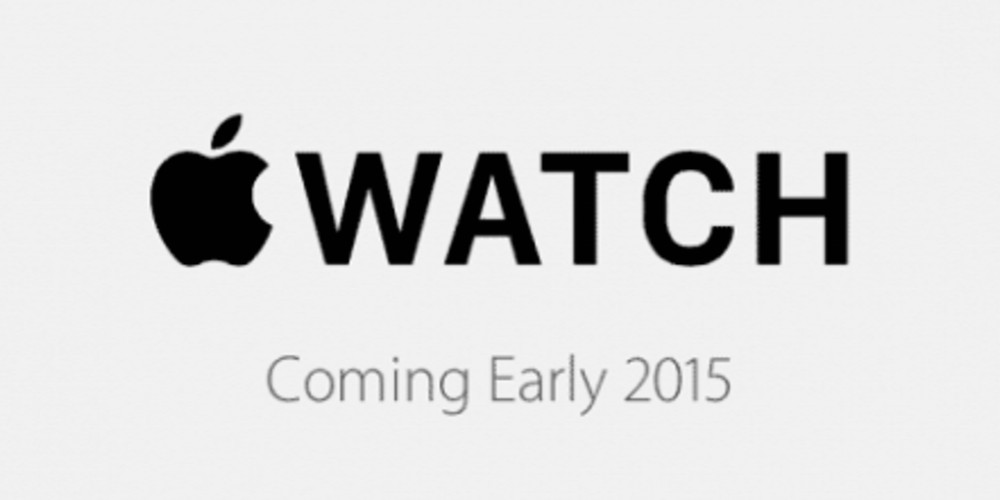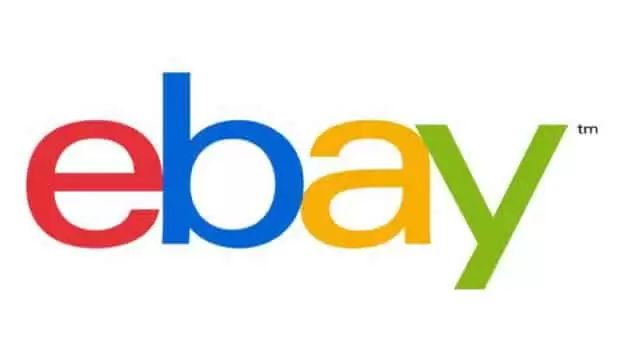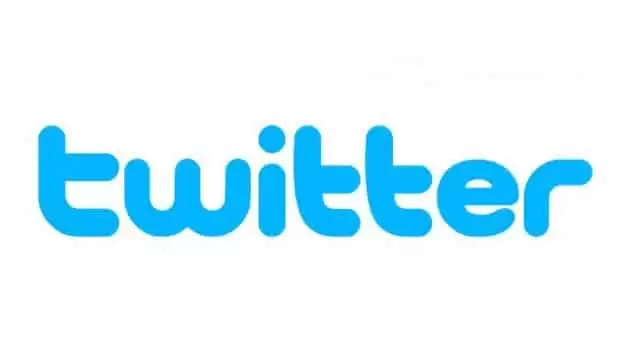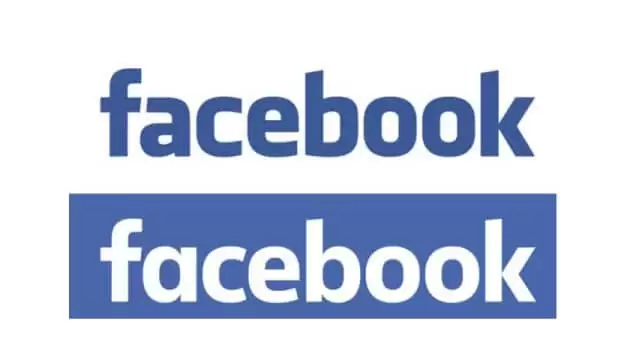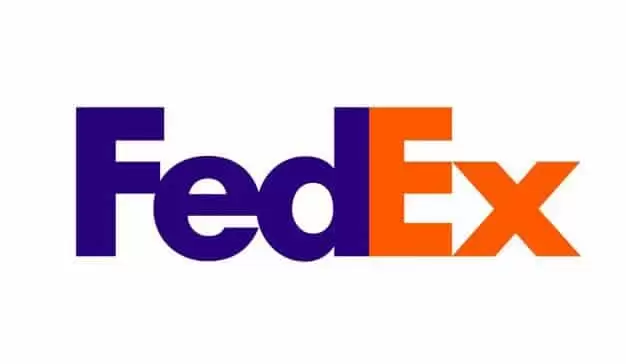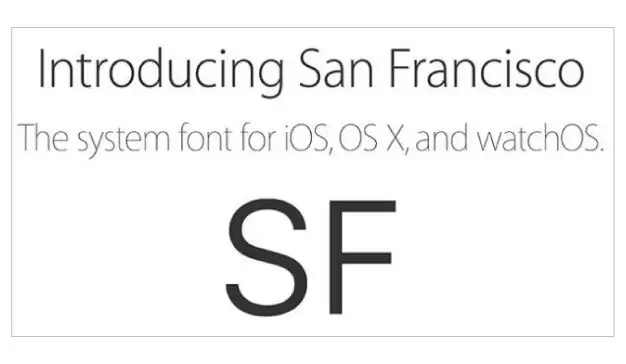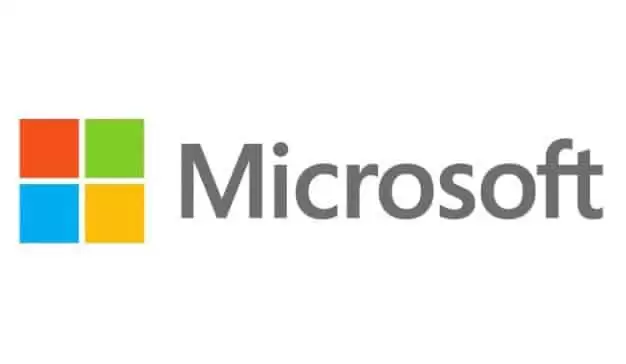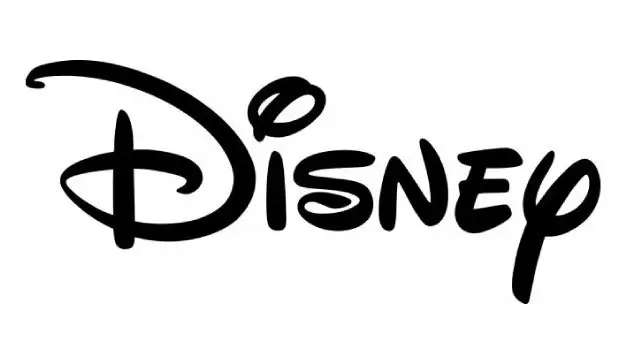
De acuerdo con el último repaso de Creative Bloq repasamos cuáles son las principales fuentes tipográficas de las marcas más famosas del mundo, con algunas particularidades entre sus historias.
Y es que, más allá de lo que generan los colores y diseños en la gente, el tipo de letra forma parte del mensaje que buscan dar desde la marca y así generar el impacto deseado entre sus clientes.
Amazon: cuenta con esa tipografía desde el 2000; es una fuente similar a Officina Sans Bold (elaborada por Erik Spiekermann), resulta clave la sonrisa que se forma por debajo de las letras.
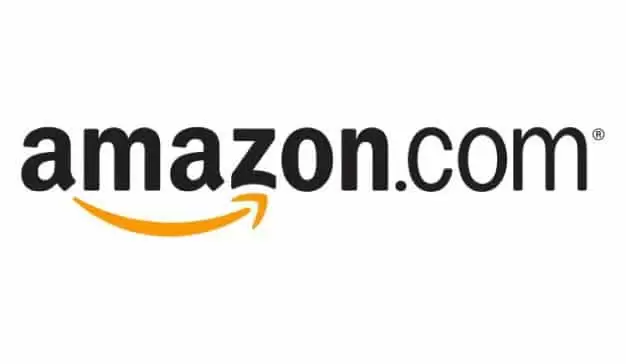
eBay: colorida, la letra es dinámica y fue diseñada por Adrian Frutiger en la década de los 60, es utilizada también en la publicidad exterior de la compañía.
Twitter: la fuente representativa se trataba de una versión modificada de Pico Alphabet, creada por la compañía japonesa Maniackers Design. Reemplazó al “pajarito” que hoy solamente acompaña.
Facebook: La última fuente la diseñó Eric Olson, de Process Type Foundry. Desde el nacimiento de la red social, el logo únicamente ha sufrido pequeñas modificaciones en cuanto al kerning.
FedEx: Es una combinación de Futura Bold con Univers 67, representa confiablidad y seriedad; es clave la flecha que se forma entre la “E” y la “x”.
Apple: fuente minimalista llamada San Francisco, está inspirada en Helvetica y DIN y hoy es de las más fáciles de identificar.
Microsoft: El logo actual de Microsoft nació en 2012 y utiliza Segoe, fue diseñada por Steve Matteson de Agfa Monotype. Microsoft utiliza Segoe y Segoe UI para sus diferentes materiales.
Disney: En el 2000, Justin Callaghan lanzó un tipo de letra freeware basado en las letras del logo de Disney llamado Waltograph. Varios dicen que se parece mucho a la letra de su creador, Walt Disney.